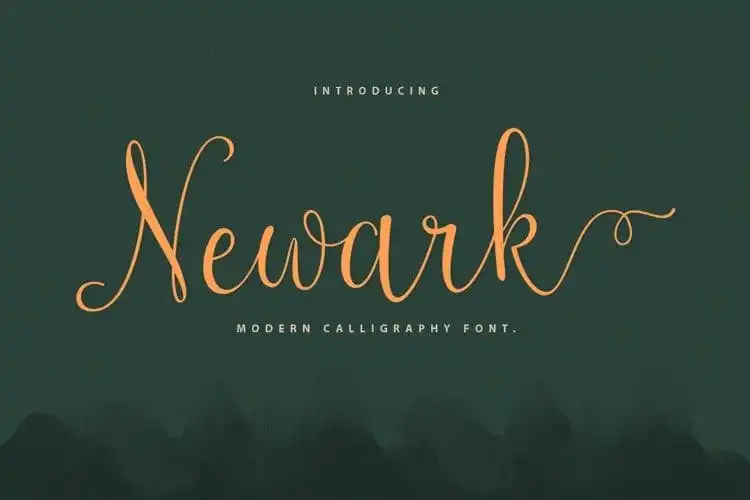
Newark Calligraphy Font – Fonte Grátis
Newark Calligraphy Font
Nova Jersey é conhecida por sua mistura arrebitada de história moderna e paisagens naturais vívidas. Introduzindo a Newark Calligraphy Font, uma tipografia de caligrafia que surgiu dessa combinação perfeita entre o passado e o presente. Com suas linhas leves e variações básicas, essa fonte traz um toque delicadamente feminino e elegante à sua criação. Ela foi criada pelo designer Sizimon em uma arquitetura moderna que se alinha perfeitamente com a estética da nova era. Perfeita para uso em marcas de moda, lojas online, blogs tendências ou qualquer negócio que deseje exibir elegância e sofisticação. A Newark Calligraphy Font é uma escolha inteligente para quem busca personalidade e classe na sua identidade visual.